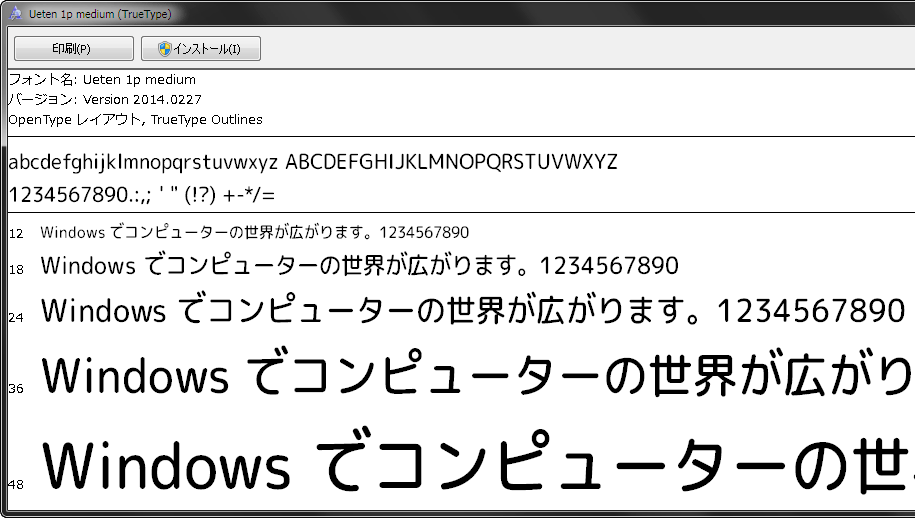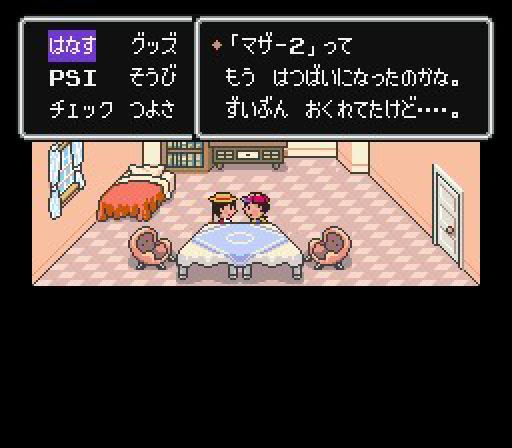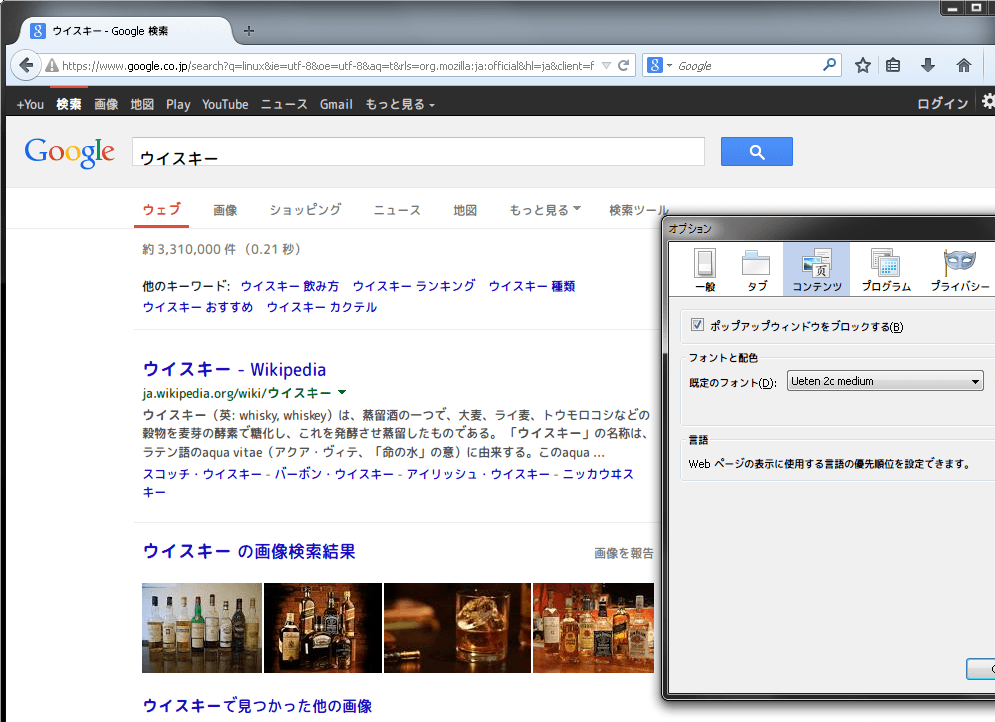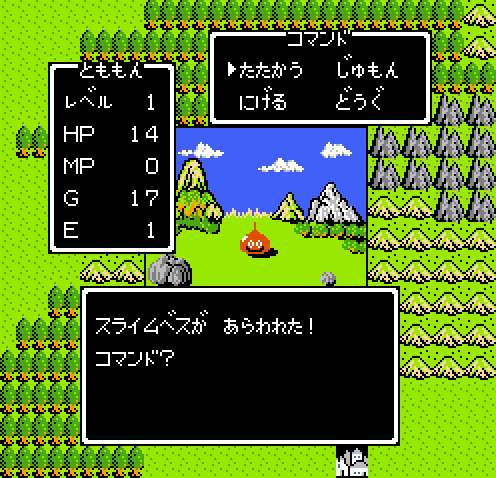
Uetenフォントを生成しましたので公開します。
特徴
- 濁点を、文字の上に付ける
- 「あ」+「゛」のような字形を収録
- 少し長体をかけた (少し縦長の字形)
- 丸ゴシック (元にした「自家製 Rounded M+」が丸ゴシックなので)
- 読みは「うえてん」フォント。濁「点」を「上」に置くので。
自家製 Rounded-X M+ 1.058.20140226 を添付のFontForgeスクリプトで変形したものです。そのため、含む字形は、「M+ OUTLINE FONTS TESTFLIGHT 058」と同じです。つまりJIS第1水準漢字はすべて含み、JIS第2水準漢字はたりないものもあります。
説明
かつて文字の上に濁点を付ける表現がありました。
ポケットモンスター赤 (ゲームボーイ版)
マザー (ファミコン版)
マザー2 (スーパーファミコン版)
こうなったのは「ファミコン、ゲームボーイ時代はメモリ容量が少ないので濁点文字グラフィックを用意できない」という理由が大きかったようですが、それはともかく今見ても、「読みやすい、判別しやすい」と個人的には思うのです。
しかし、それを目指して実際に作ってみたPixelMplus http://itouhiro.hatenablog.com/entry/20130602/font をUnityアプリに組み込んでスマートフォンで表示してみると、最近の解像度のゲームにはどうもマッチしてないです。アウトラインフォントのほうがよい感じです。
そこで、アウトラインフォントで濁点を1行上に置いた、このフォントを作りました。
ゲーム向けに作りましたが、意外にWeb表示にもおもしろいかも。文字の上のほうがスペース空きます。濁点用にスペースをとっていますので。
あと、濁点・半濁点を「あ」~「ん」にもつけました。Unicodeには通常の濁点・半濁点とは別に「連結用 Combining」濁点・半濁点がありますので、「あ」+「連結用濁点」を入力すると、「あ゙」と表示されるようにリガチャー設定してあります。文字自体はUnicodeの私用領域(外字領域)に置いて、「GL-アンチック」 http://gutenberg.sourceforge.jp/ja/license.html と同じコードポイントにしました。外字としても使えますが、連結用濁点として使うこともできます。